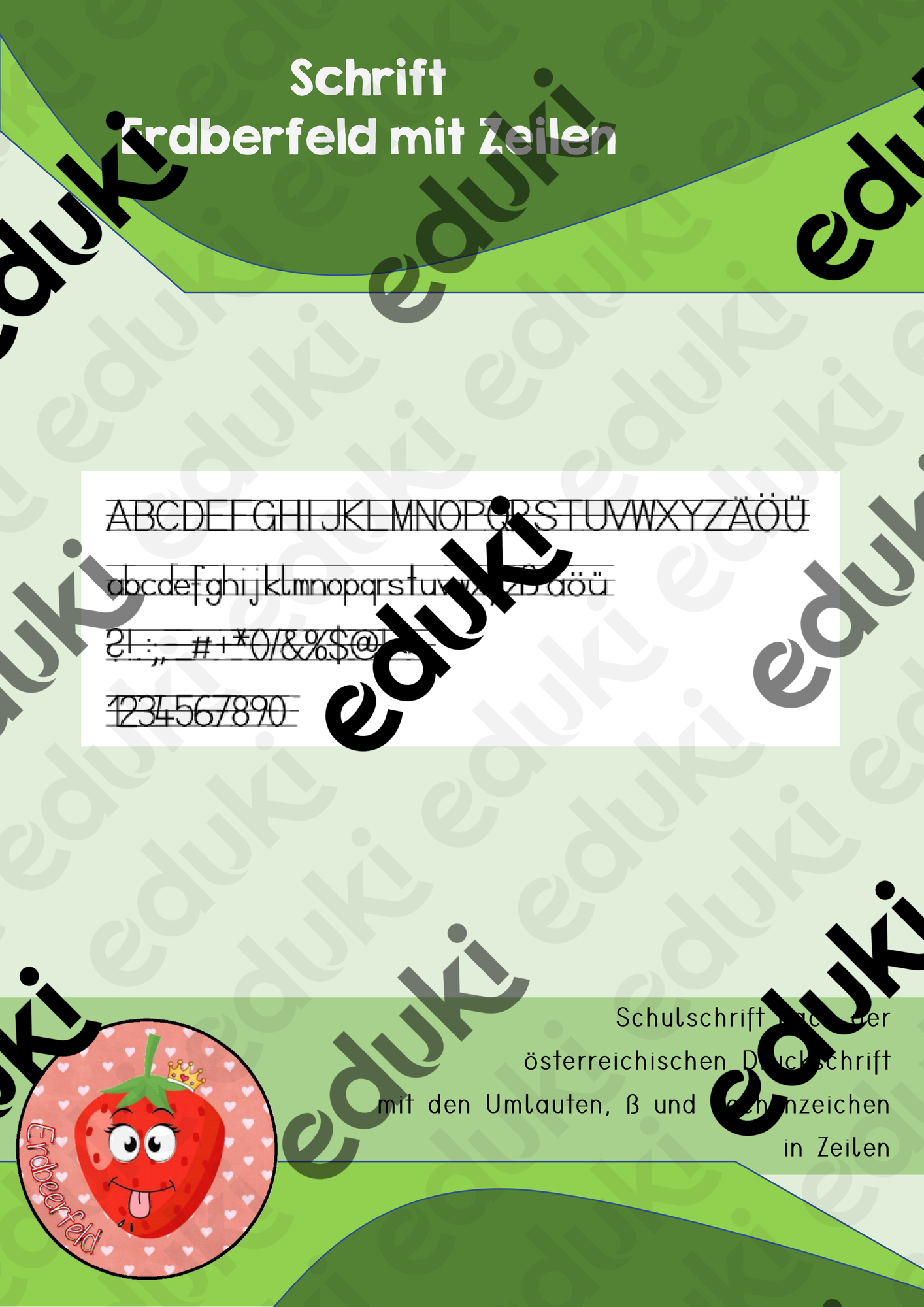
Passend zur Schrift Erdberfeld1 hier auch die Druckschrift in Zeilen.
Ich habe wieder besonders darauf geachtet, dass das f unter die Zeile geht, das l endlich mal sein Häkchen hat, das ß und die Umlaute ö ü ä auch mitspielen dürfen usw.
Angepasst ist die Schrift auf die österreichische Druckschrift.
Gut geeignet für Abschreibübungen, Schönschreibübungen und ähnliches.
Schriftart Erdberfeld in Zeilen